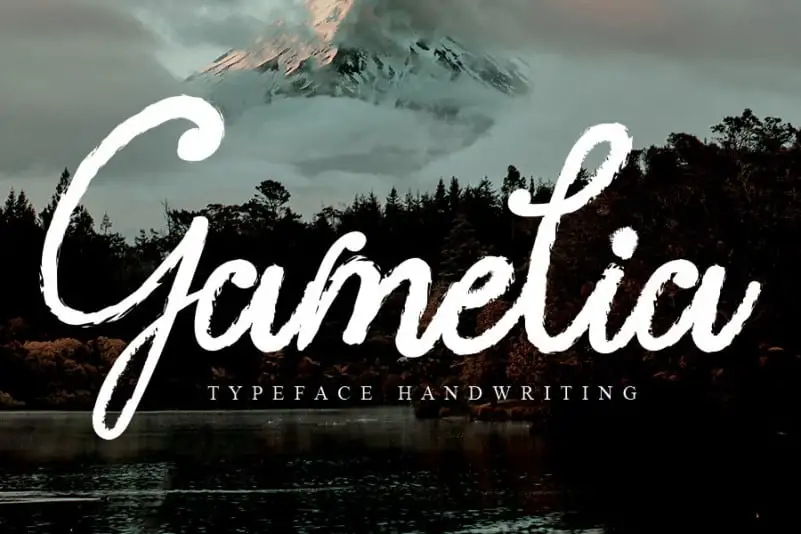
Gamelia Script Font – Download Grátis
A Gamelia Script Font é uma escolha incrível para os designers que buscam uma fonte com estilo único e elegante. Inspirada no estilo antigo mas atualizada com a modernidade dos traços de pincel, essa fonte dá um toque sofisticado em qualquer projeto visual. Seja para criar cartões de visita profissionais, gráficos publicitários ou até mesmo designs de adesivos personalizados, Gamelia Script é uma excelente opção. Seus traços leves e delicados complementam a coragem do design, criando texturas que dão vida aos seus projetos digitais. Com Gamelia Script Font, você não precisará usar mais qualquer outra fonte, pois essa combinação de estilo e simplicidade se destaca como uma opção inovadora para sua próxima criação gráfica.